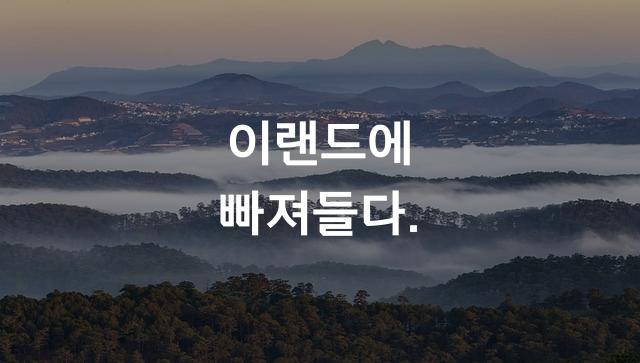
이랜드 나이스체는 각진 바탕과 장식체를 조화롭게 결합한 제목용 폰트입니다. 강렬하면서도 세련된 인상을 줍니다.
이랜드 나이스체은(는)
바탕 스타일, 명조/전통, 장식 스타일, 네모꼴, 단단함, 별모양/패턴, 길고/크고 계열의 생김새를 가지고 있으며
제품 포장, 카페 메뉴, 소셜 미디어 등에서 자주 활용되며, 효과적인 메시지 전달에 적합합니다.
이 폰트는 음식/식음료, 라이프스타일, 소매/유통 분야에 잘 어울리며,
친근한, 귀여운, 재미있는 느낌을 담고 있는 것이 특징입니다.